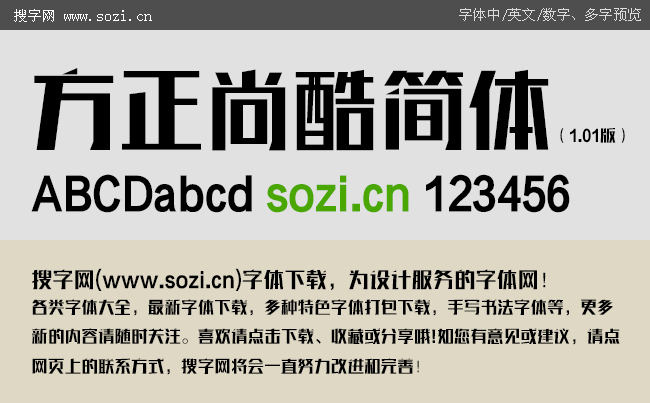
方正尚酷簡(jiǎn)體
搜字網(wǎng)提供一款方正尚酷簡(jiǎn)體中文字體下載,方正尚酷簡(jiǎn)體字體重心上移,筆畫(huà)棱角分明,字形酷炫,給人一種時(shí)尚酷炫質(zhì)感。適合書(shū)籍設(shè)計(jì)、展板設(shè)計(jì)、海報(bào)設(shè)計(jì)等廣告設(shè)計(jì)場(chǎng)合使用。